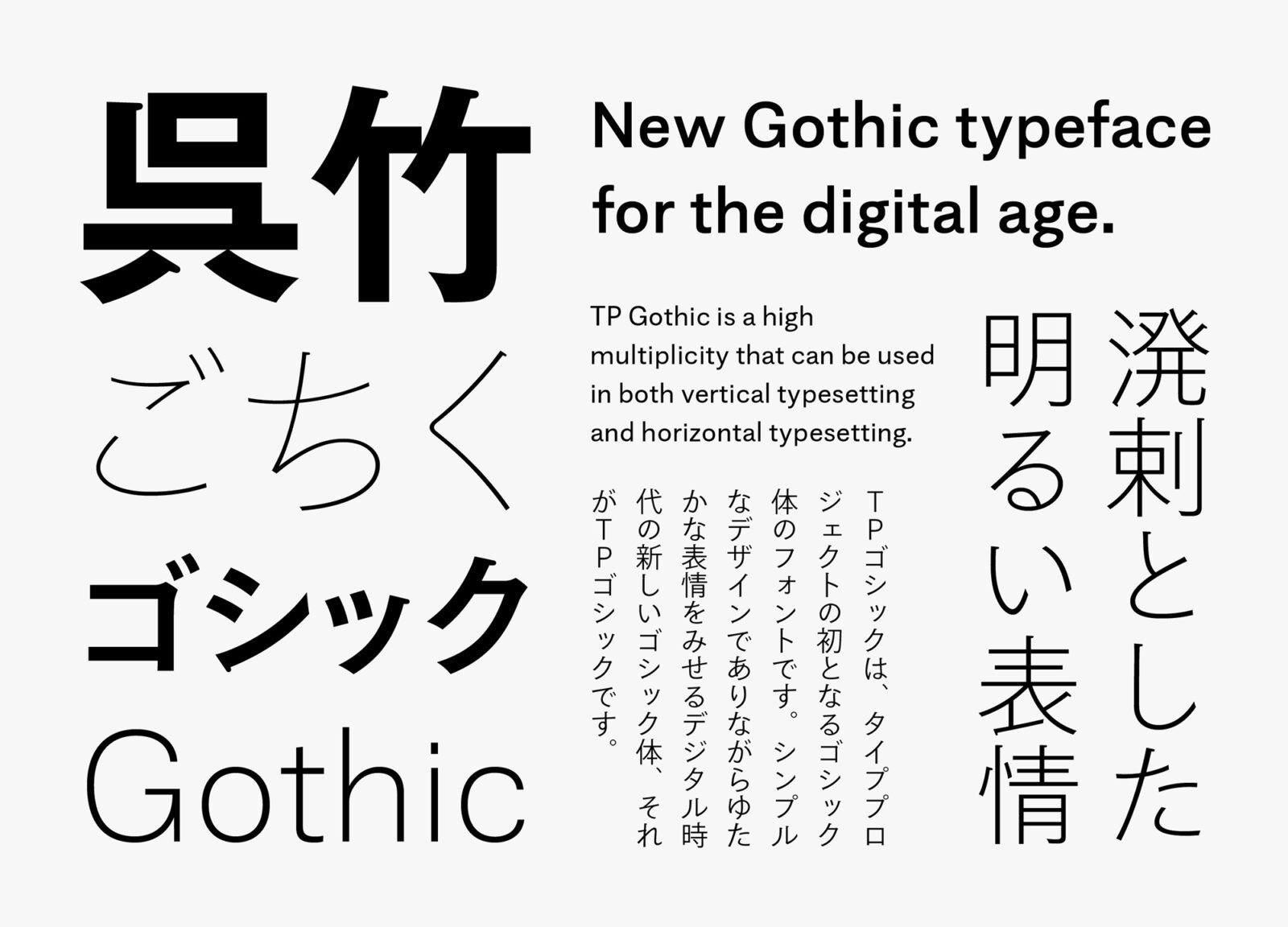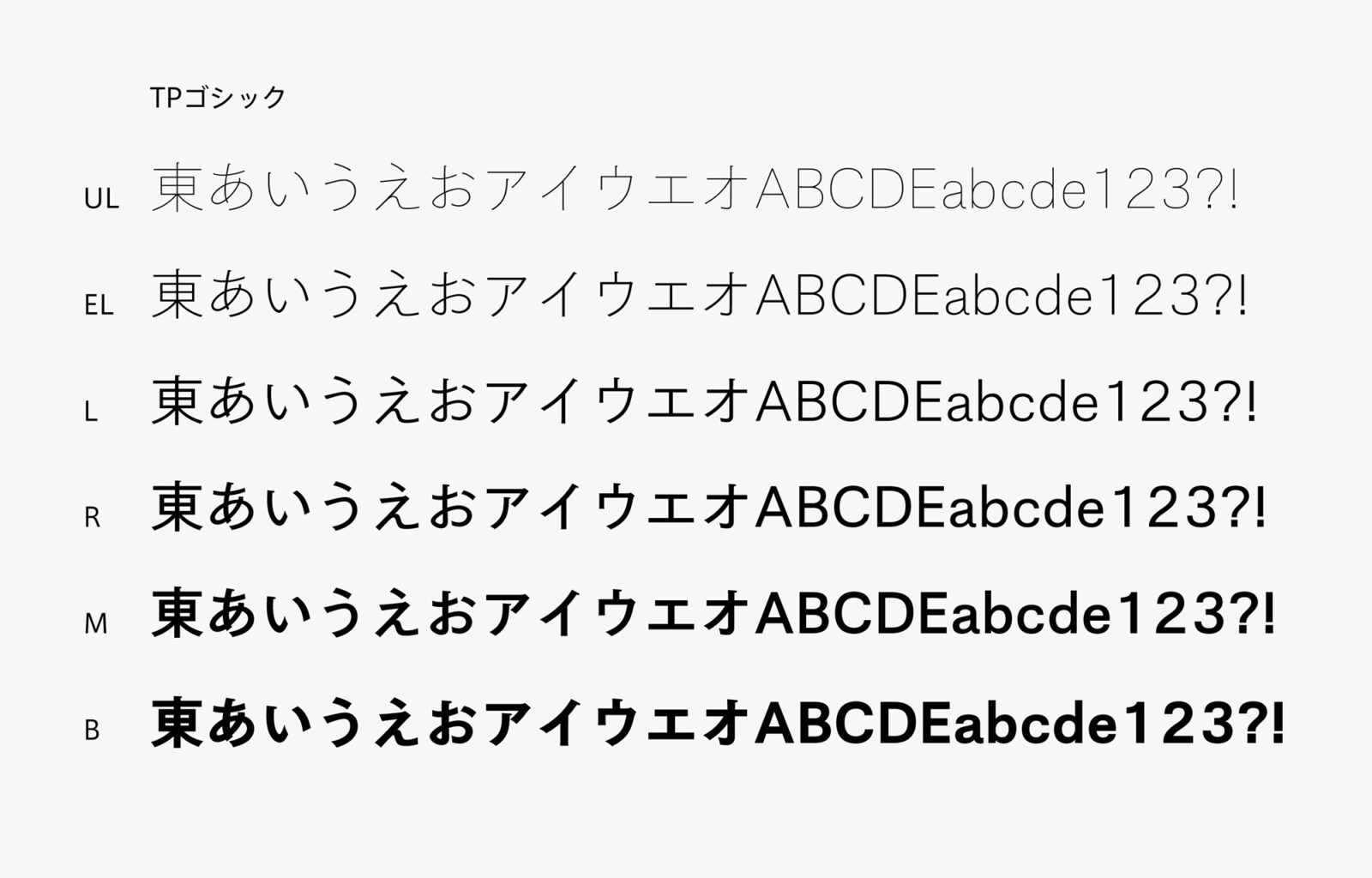
タイププロジェクト、初となるゴシック体フォント 「TPゴシック」の提供を開始
縦組みでも横組みでも安心して使える汎用性の高いオーソドックスなゴシック体
TPゴシックは、TP明朝の仮名にちかい線質をもちながらもモダンに寄りすぎず、溌剌とした明るい表情をもつ縦組みでも横組みでも安心して使える汎用性の高いゴシック体です。簡素なアウトラインで筆画が表現されているため、さまざまな解像度で安定した表示結果を得られます。タイププロジェクトのフォントに通底する「デジタル環境に最適な書体ファミリー」というテーマを、ゴシック体のカテゴリーで実現しています。
TPゴシックはニュートラルな印象の書体ですが、起筆部のセリフやストロークの抑揚、ハライの抉り(えぐり)の効果で、ゴシック体に求められる力強さもそなえています。フトコロを絞り気味に設計した漢字は、端正で落ち着いた印象を与えます。仮名は全体的に小ぶりな字面で、縦で組んだときの文字の流れを重視するとともに、横組みでの筆勢と安定した字並びを両立させるための検証を行いました。書体開発の初期段階から高頻度ですり合わせをおこなった和文と欧文の相性の良さは、TPゴシックの持ち味を引き出す重要な要素になっています。
タイププロジェクトの代表取締役 鈴木 功は、「ゴシック体はサンセリフ体と同類のカテゴリーで扱われる場合もありますが、区別したほうが正確といえると思っています。TPゴシックは、以前から新しさと品質をかねそなえた和文ゴシックがほしいという声を耳にしていたこともあり、ゴシック体カテゴリーのまんなかを射ぬくデザインでその要望に応えようと考えました。オーソドックスな書体設計を採用し、高い品質をめざしたわけですが、その結果、当初われわれが想定していた以上に使い勝手のよい書体ができあがりました」と述べています。
TPゴシックのウエイトファミリーは、UL (ウルトラライト)、EL(エクストラライト)、L(ライト)、R(レギュラー)、M (ミディアム)、B (ボールド)の6 ウエイトです。太いウエイトほどストロークの抑揚が大きく強い印象を与えますが、細いウエイトでもゴシック体特有の雰囲気をかもしだします。オーソドックスなゴシック体でありながら、新鮮な空気を演出するTPゴシックは、さまざまな場面で活用することができるデジタル世代の書体ファミリーです。